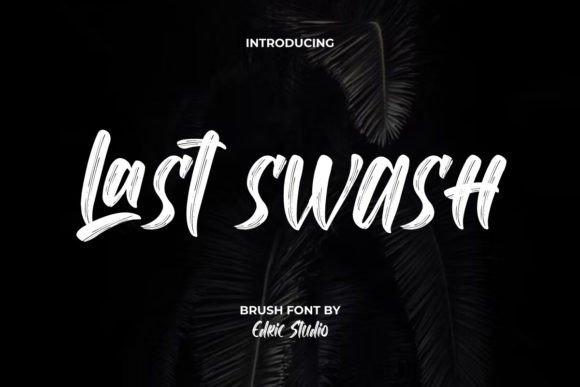
Last Swash
適切なデザイン要素を見つけるのは難しい場合がありますが、Last Swashは作品を即座に引き立てる優れたコレクションを提供します。
POD(オンデマンド印刷)製品、結婚式の招待状、またはソーシャルメディアのグラフィックを作成している場合でも、Last Swashは理想的です。